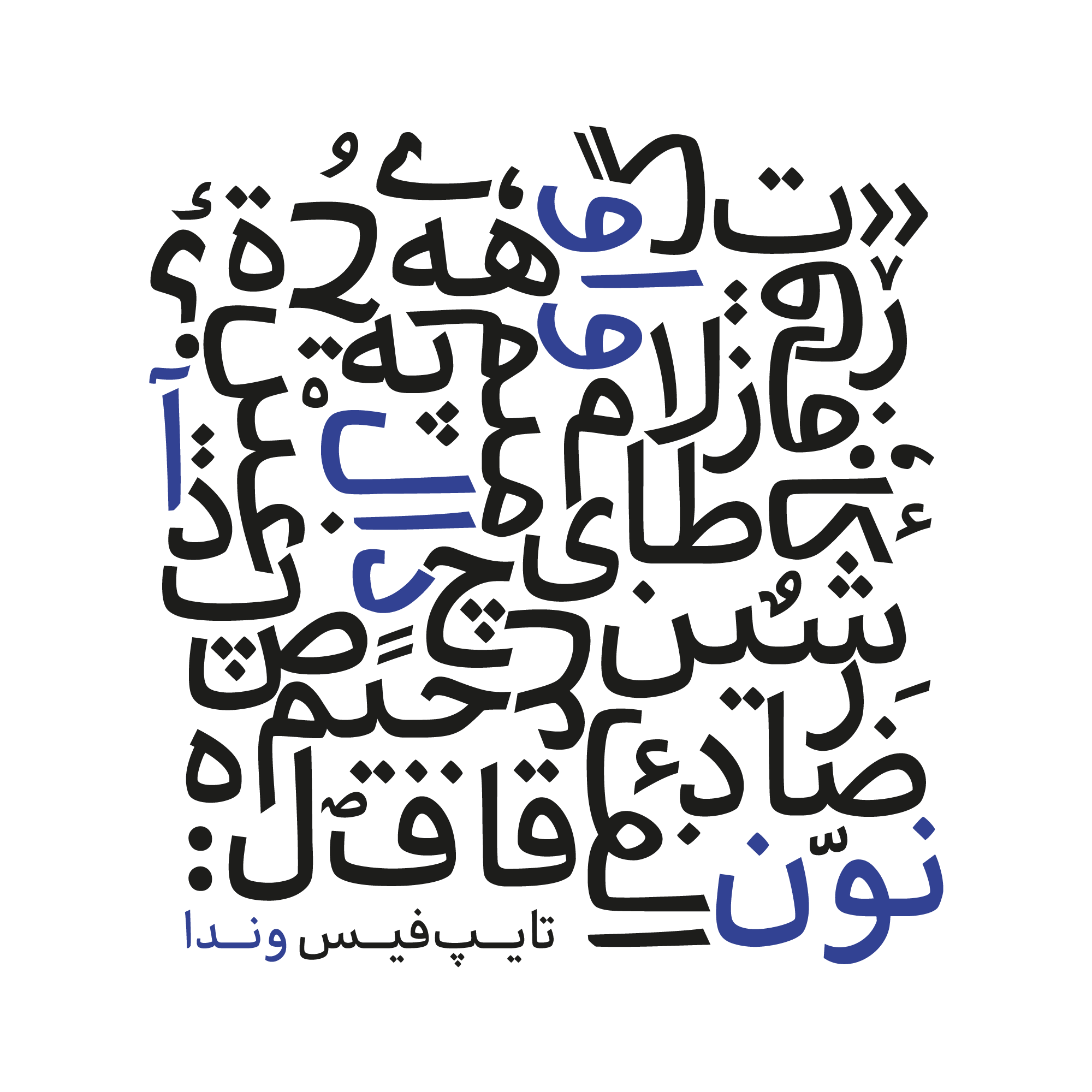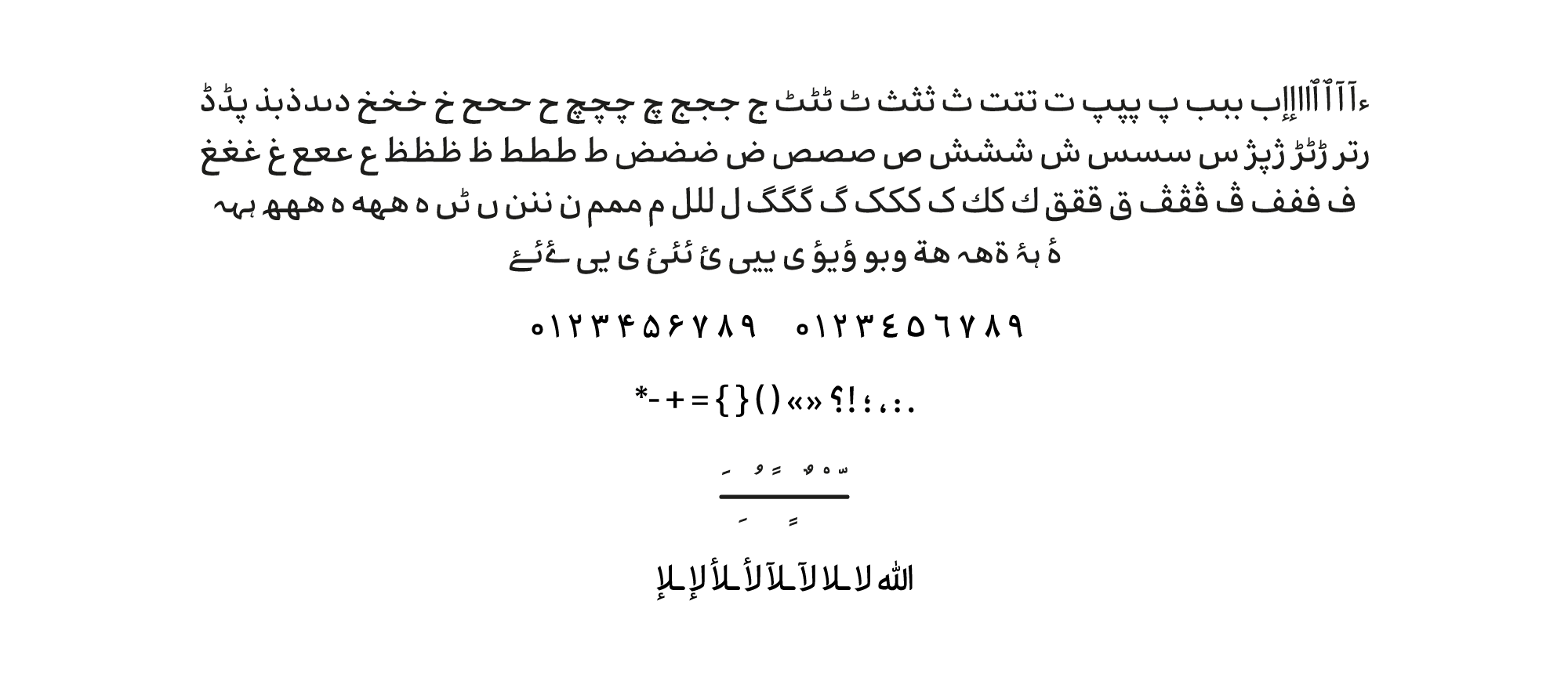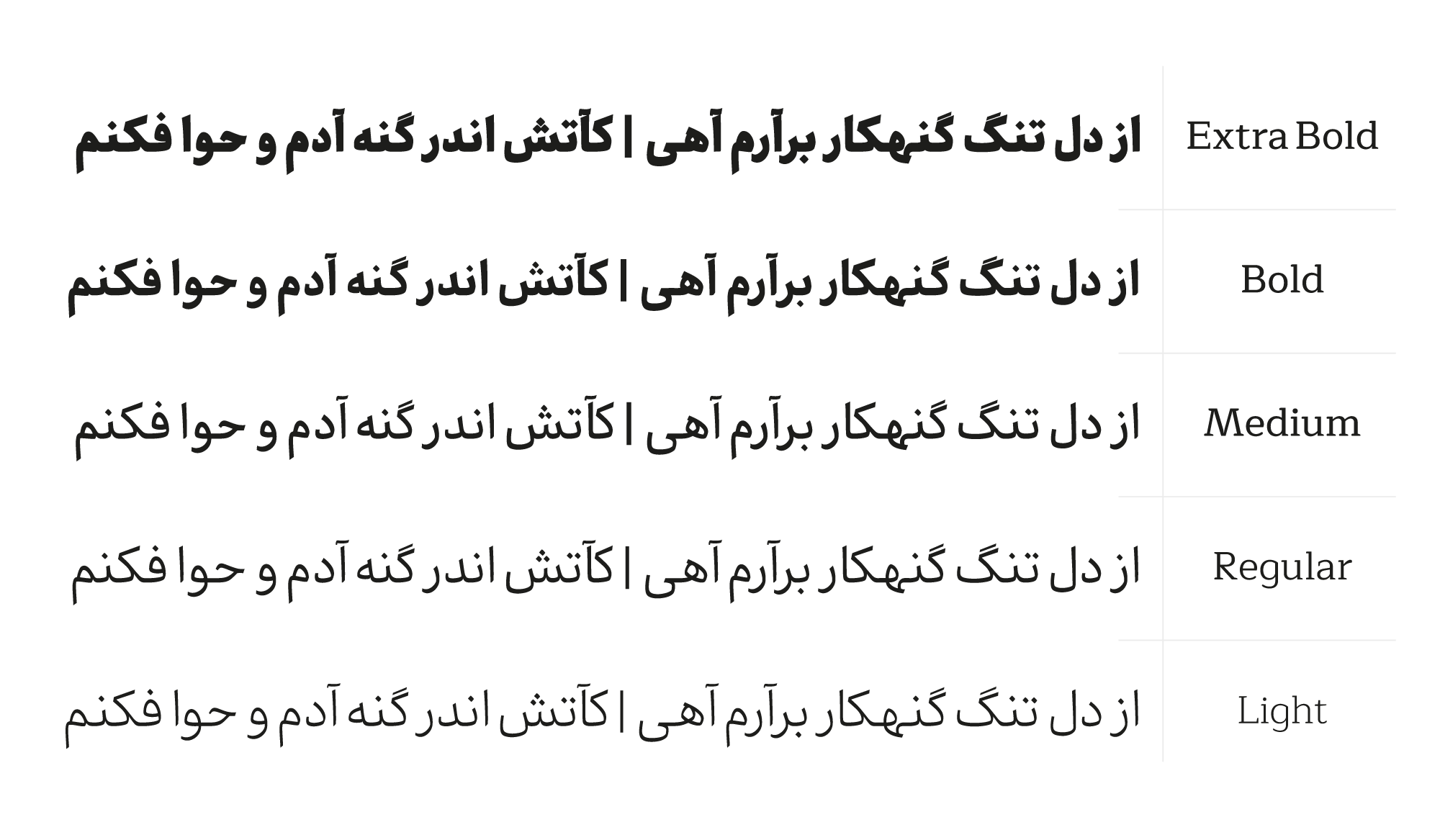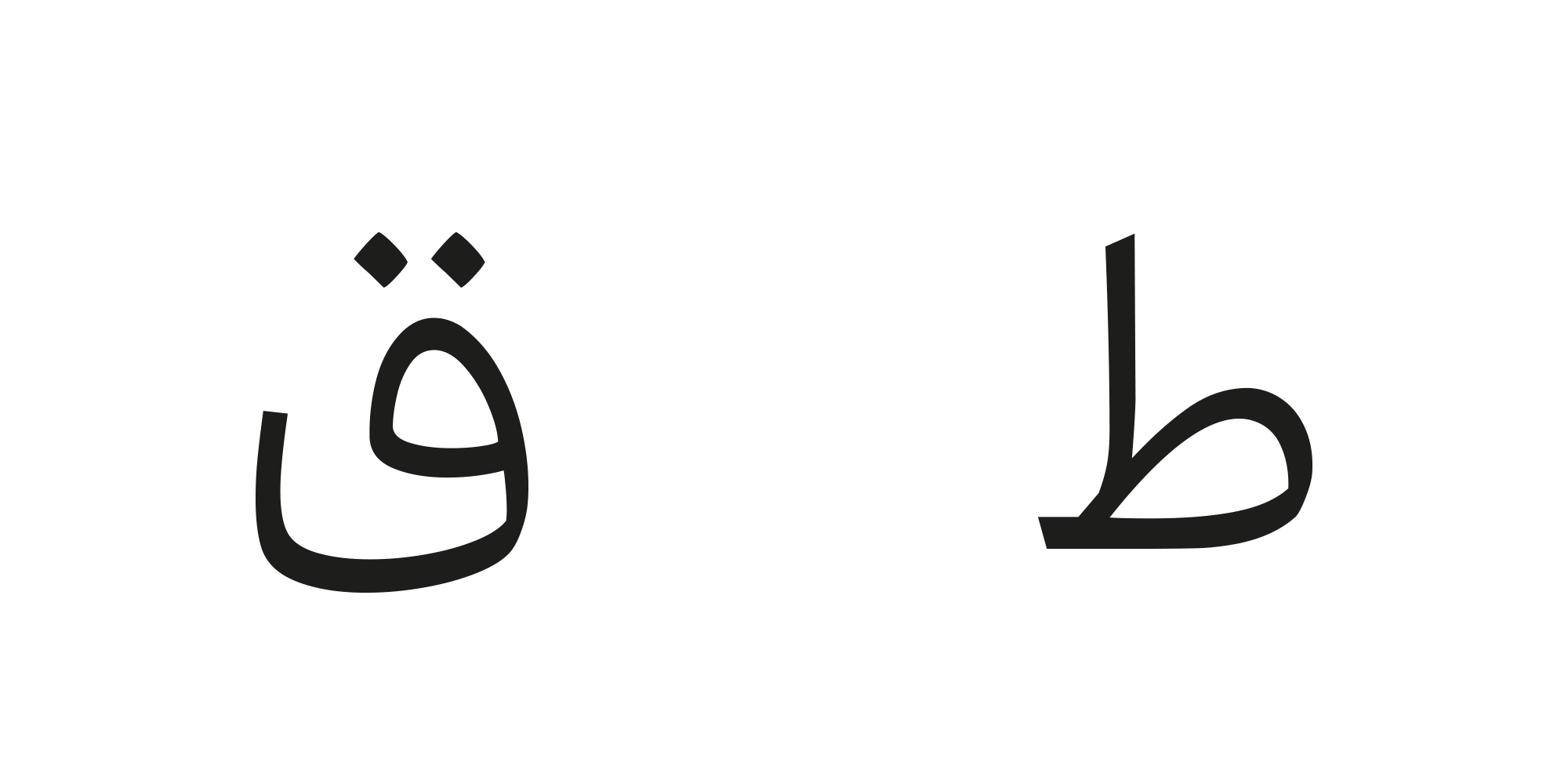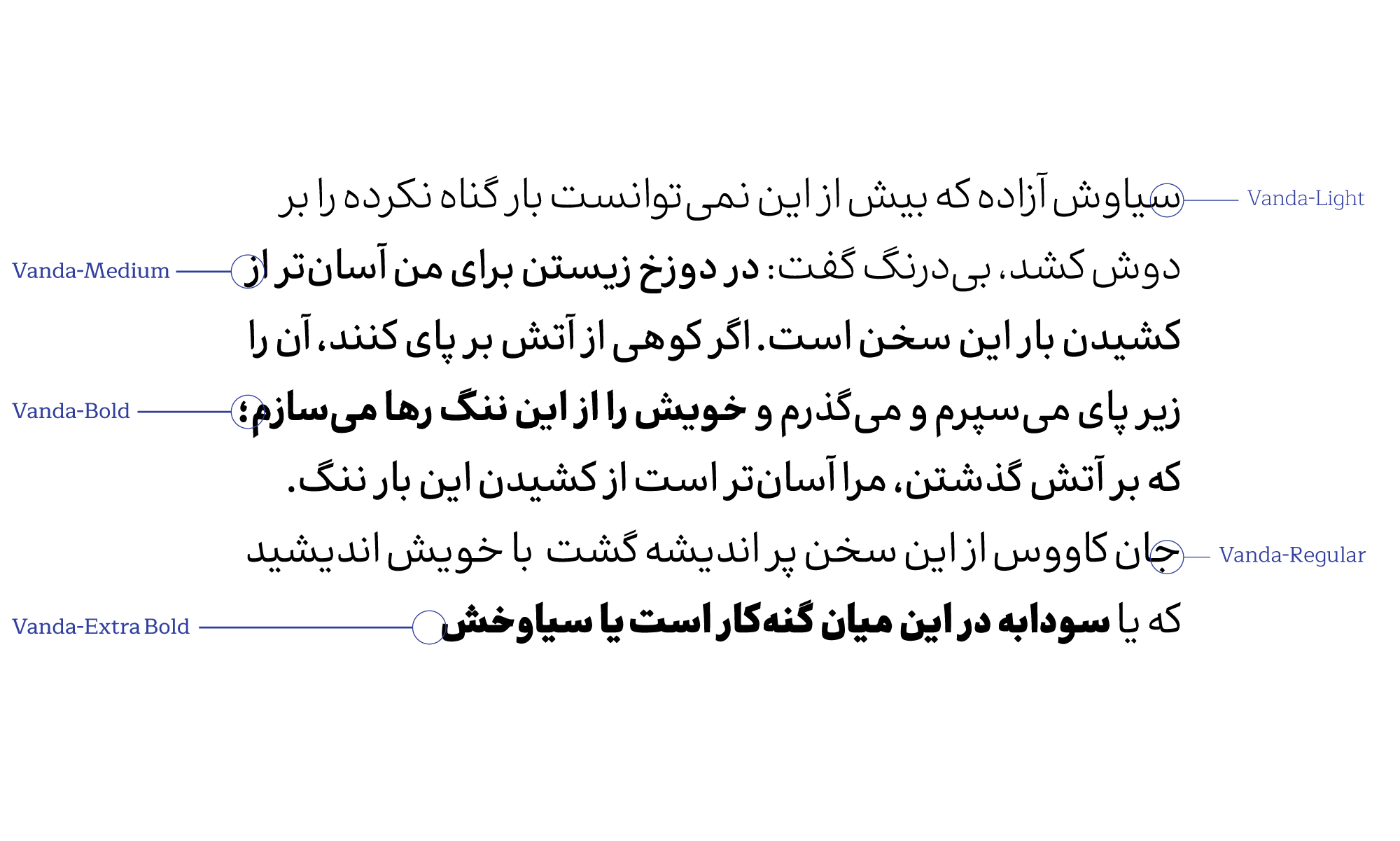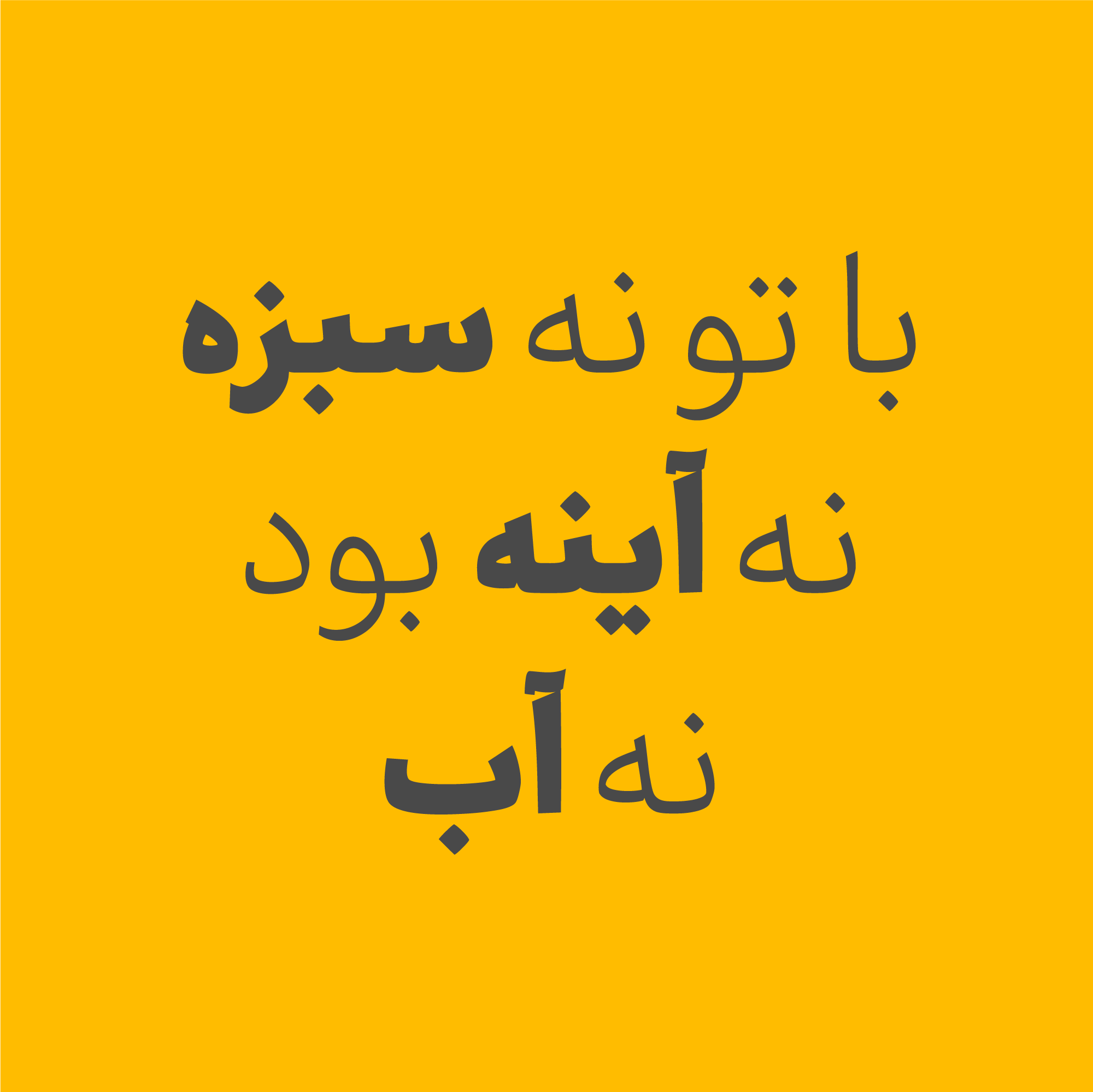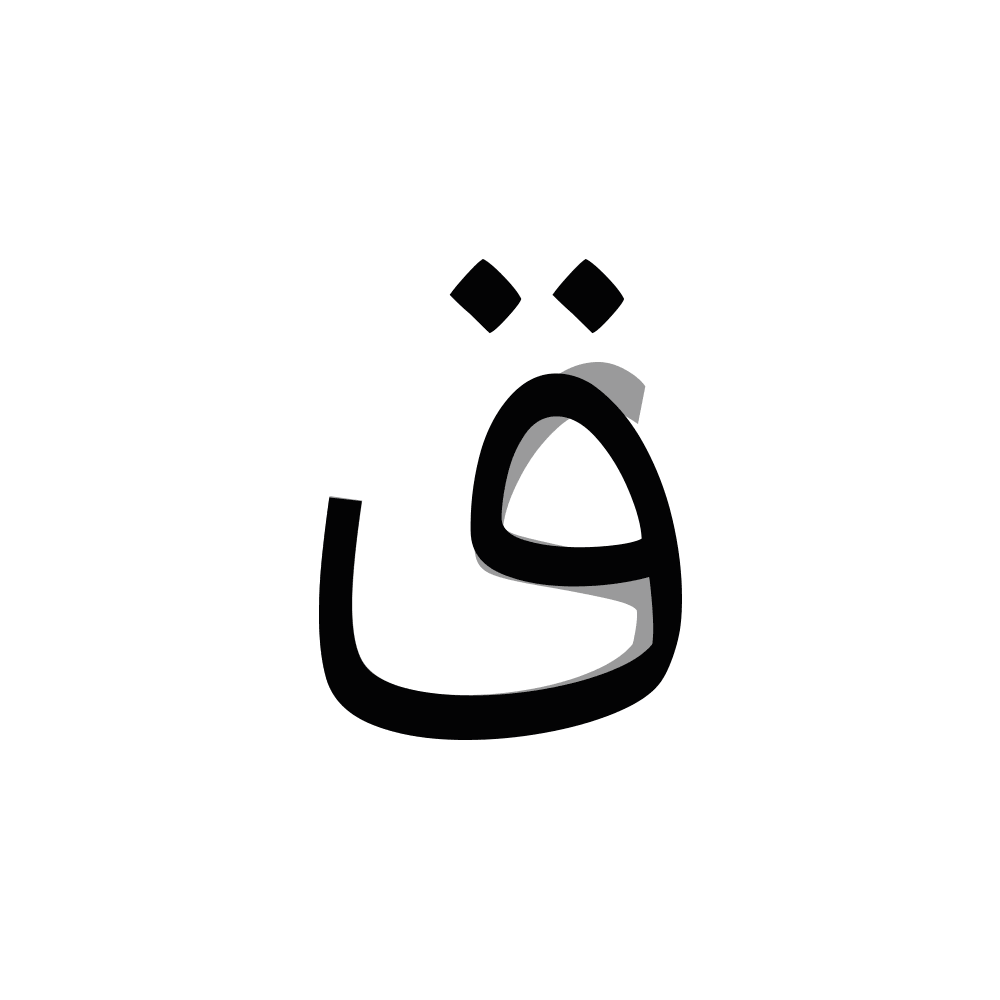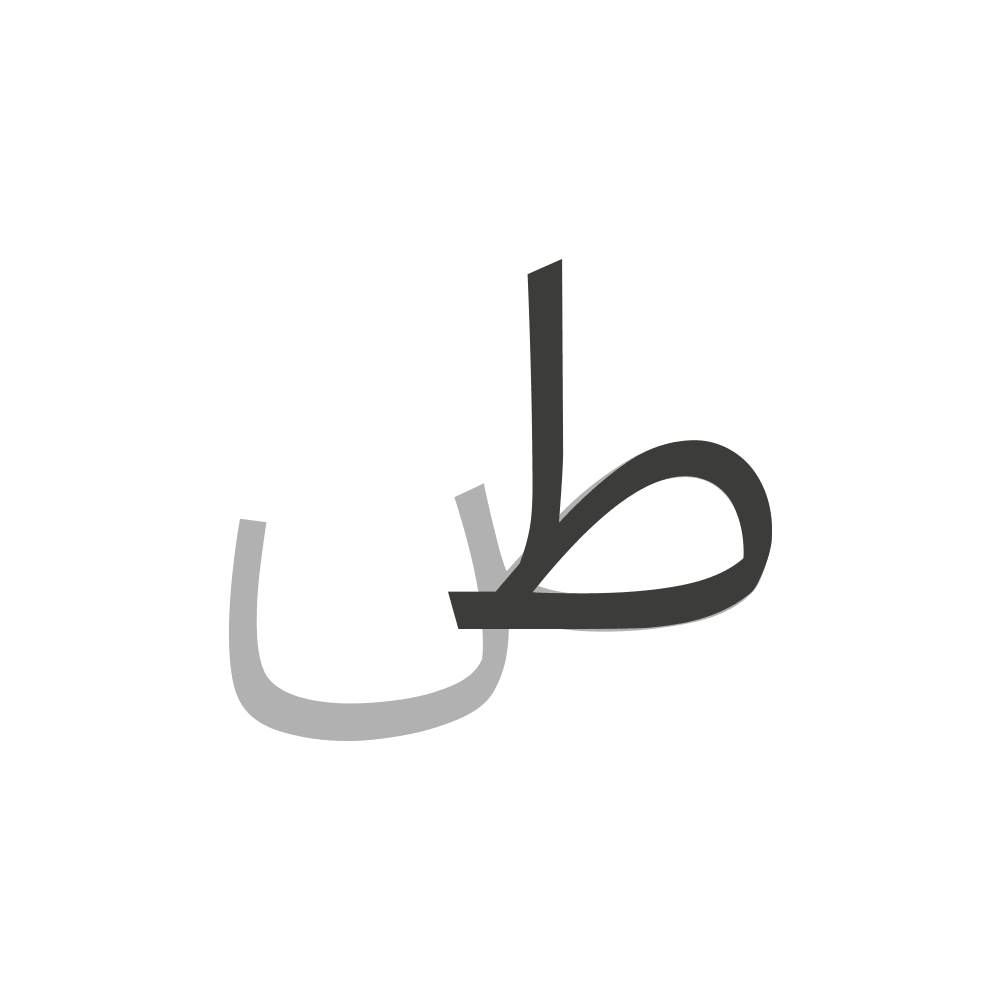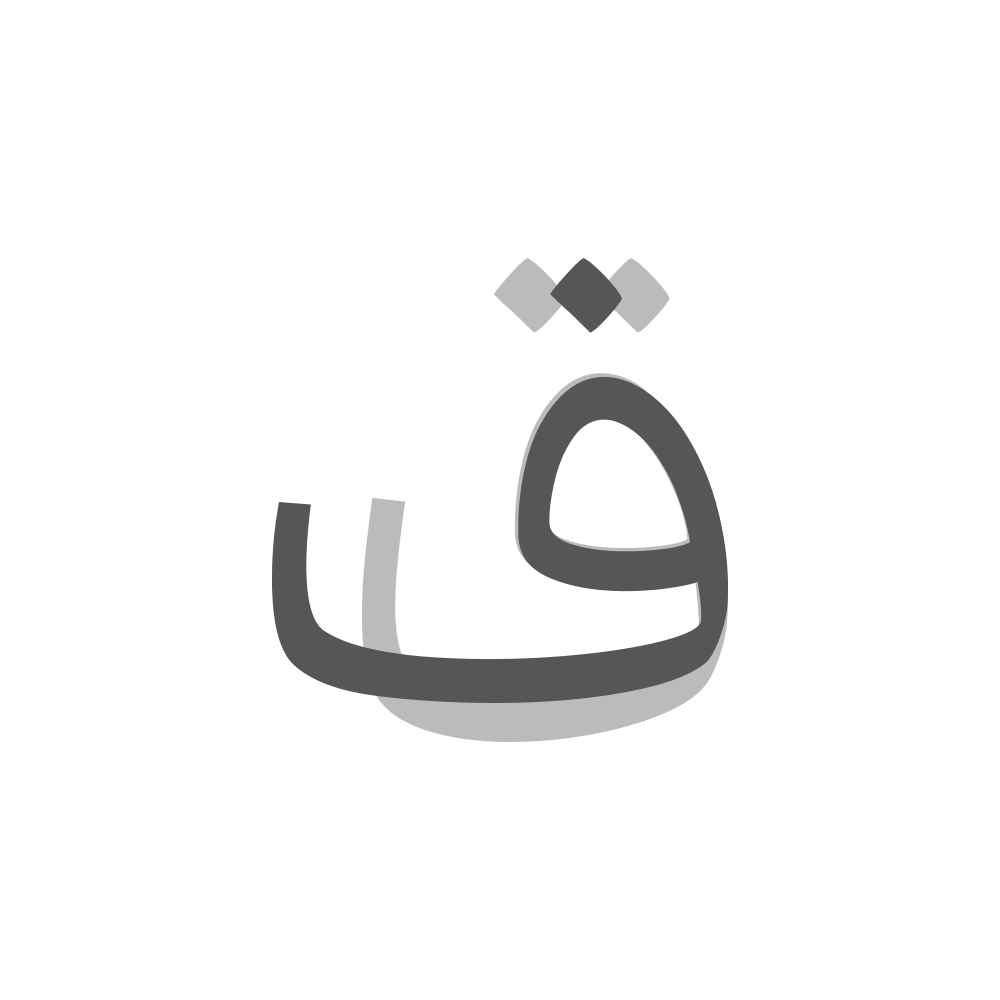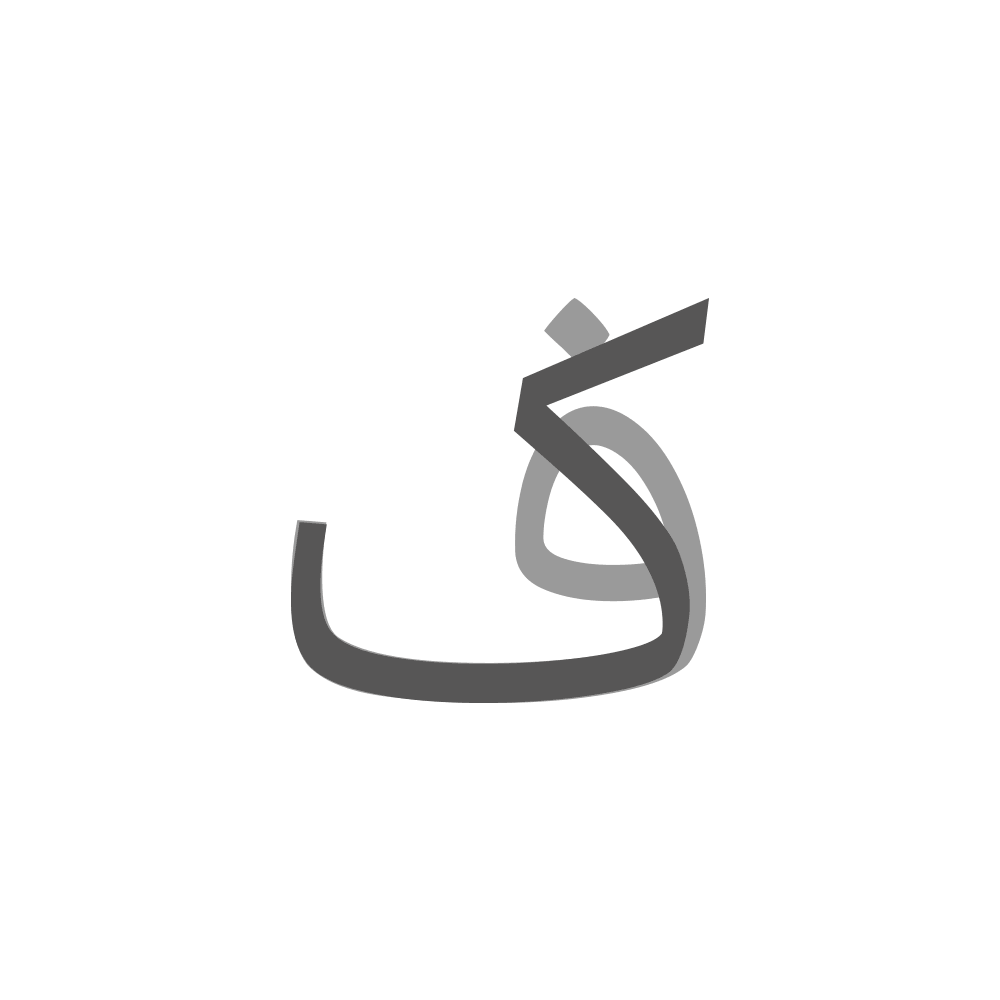
فضاهای منفی محصور در مقایسه با فضاهای مثبت و منفی غیر محصور موکدتر و هویداتر هستند. این انتخاب برای افزایش قدرت خوانش (Readability) و میزان تفکیک و تشخص بصری کاراکترها (Legibility) در سایزهای کوچکتر صورت گرفته است.
ارتفاع کاراکترها متعادل است. محدوده پایین خط کرسی (Descender) کوتاه و کاسهها کمعمق هستند. حضور فرمها در فضای بالای خط کرسی (Ascender) پررنگ است، این تمرکز در خوانش متنهای طولانی نقش مهمی دارد.
تطابق فرمها در فونت وندا
توجه به تطابق و شباهت فرمها، به عنوان یکی از شاخصهای دیزاین در نظر گرفته شده است.
عربی، پشتو و کردی
فونت وندا از زبان فارسی، عربی، کردی،پشتو و انگلیسی پشتیبانی میکند.
تکرار زوایا
کشیدگی
تایپفیس انگلیسی پیشنهادی
تایپفیس Maitree از لحاظ فرم با تایپفیس وندا مشابهت دارد. این فونت در گوگل فونتس قابل دسترسی است. همچنین جهت سهولت استفاده در فونت وندا نیز قرار دارد.